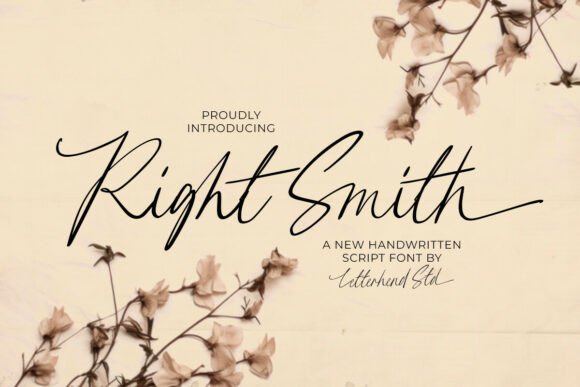
Right Smith
Việc tìm kiếm các thành phần thiết kế phù hợp có thể là một thách thức, nhưng Right Smith cung cấp một bộ sưu tập đặc biệt giúp nâng tầm công việc của bạn ngay lập tức.
Được chế tác với độ chính xác cao, Right Smith cung cấp các vector sạch, kiểu chữ mượt mà và giấy phép thương mại để bạn yên tâm.